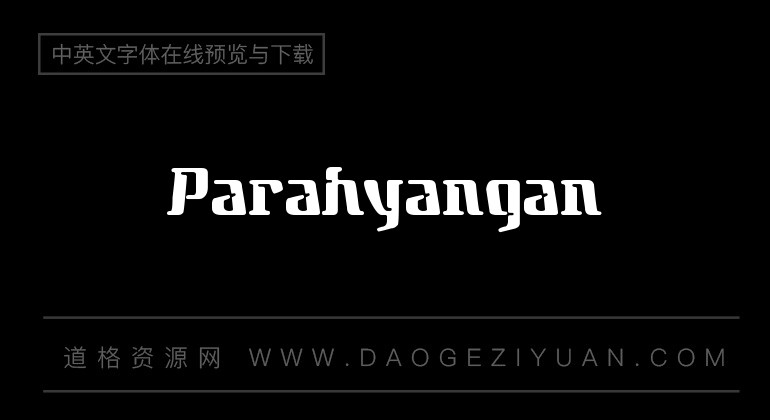
? Parahyangan 字体是一种简约、现代化的印尼文字体。它由设计师 Adhitya Ramadhan 创作,旨在为印尼文提供一个新的视觉形式。它的字体特点是简洁明了,字形清晰,拥有良好的可读性,同时又具有独特的文化色彩。此外,Parahyangan 字体还具有跨文化传播的能力,可以用于多种语言。内容介绍
Parahyangan是一款非常不错的手写艺术字体,具有很好的视觉感,适合于文化类的宣传设计、商业类品牌的广告和产品包装设计以及个性化文字排版等较多场景。